「テレビマガジン完全復刻コレクション マジンガーZ」は、「テレビマガジン」のマジンガーZ付録&口絵を完全復刻した、あの懐かしいトランプも、ワクワクしたポスターも、もう一度楽しめる、ファン垂涎の一冊。
「テレビマガジン」編集担当・「テレビマガジン完全復刻コレクション マジンガーZ」完成までの独占手記
2018~2019年にかけて、永井豪の画業50周年を記念した展覧会や映画など、さまざまなイベントが行われ、雑誌連載時の雰囲気を味わえる関連書籍も各社から発売された。「
「テレビマガジン完全復刻コレクション マジンガーZ」も、「読む」楽しさに加えて、「美しい資料」としての性格を兼ね備えた、復刻本としては最強の作りをめざして制作された。
復刻本の編集は想像以上に手間と費用のかかる作業となる。原本をバラしてスキャンして進めることが多いが、この本は、雑誌が貴重なこともあり、バラさずに作業していった。そのためノド(中央)が歪んでうまくスキャンできないため、別にカメラで撮影し、画像を合成してページデータを作ることから始めた。
さらにそこからは「汚れ」「掠れ」「滲み」「色味」との戦いだった。ゴミや折れ目などの「汚れ」を消し、時間とともに消えた文字、インクのノリが悪くて見えにくかったりするイラストの「掠れ」を当時を想像して復元。インクの「滲み」により、ガタガタになったコーナータイトルや本文の文字、イラストなどのフチをフラットにしていく。そして、劣化によって色が薄くなったページをオリジナルに近づけ、モアレが出ないようにしながらシャープネスをかけてかつての雑誌と同じような「色味」を出していった。
修復するのは雑誌のページだが、実はそのように見える一枚の画像。当時のコーナータイトルは、ほとんどが手書きで文字として打ち直すことができない。本文も当時使われていたフォントは、現在流通しておらず、ページを再現するには一文字ずつ(に見える画像を)修整していかねばならなかった。
通常はこれらの作業を突き詰めて復刻本は完成だが、ここでとんでもない罠が待っていた。古い雑誌の青インクを使った1色ページにありがちなのが、裏のページが透けてしまう、いわゆる「裏写り」がひどいページ。まるでページに油をこぼしたかのような透け具合で、何が描かれているのか判別すら難しいページが多数存在していた。この修復にとんでもない時間と費用がかかってしまった。
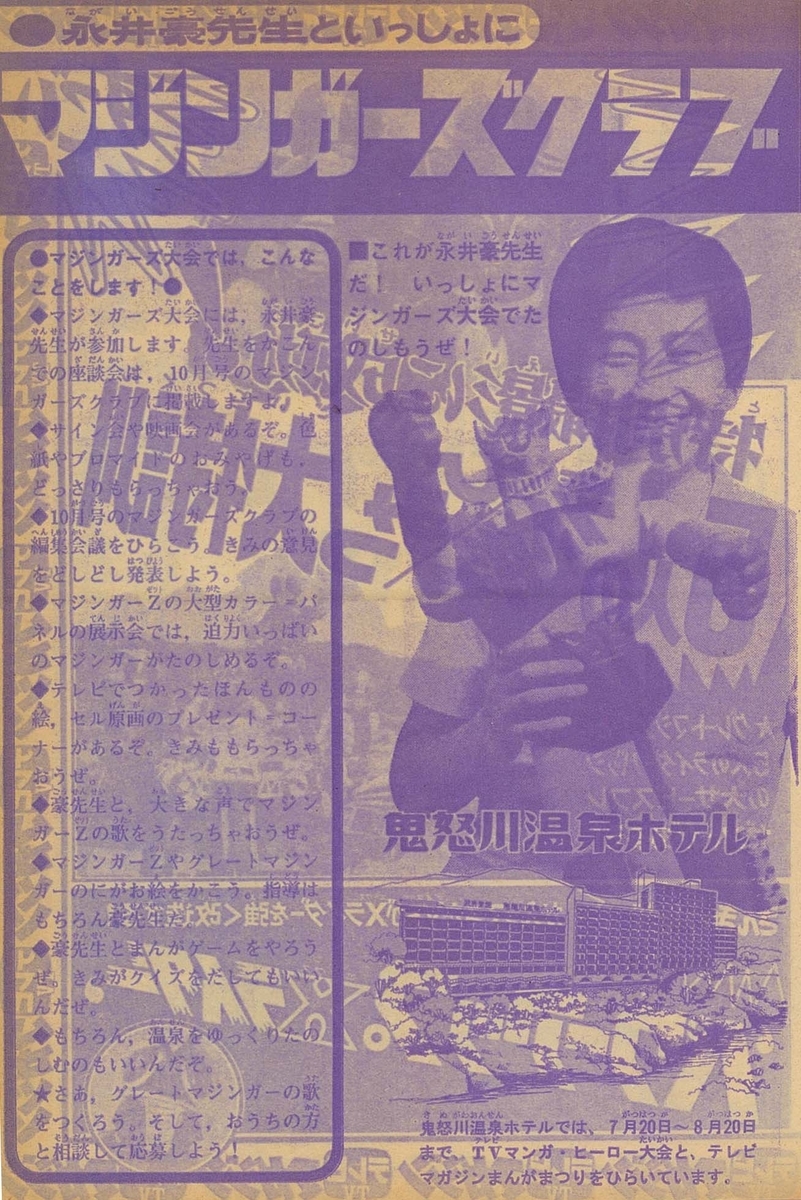
そのうえ、綴じ込み付録を当時と同じ大きさ、同じような紙質で一冊に組んでみたところ、本を閉じたときに厚紙のフチの跡が他ページについてしまったり、本を開くとページが剥がれすくなったりすることが判明した。残念ながらすべての付録を綴じることを断念。最終的にいくつかの付録は厚紙のケースに収納して届けることになった。
そのような苦難を経て完成した「テレビマガジン完全復刻コレクション マジンガーZ」は、「テレビマガジン」を読んでいたあの頃に返って記事を読め、付録を組み立て、ポスターを広げ、機械獣トランプで遊んでいただける究極の一冊となる。